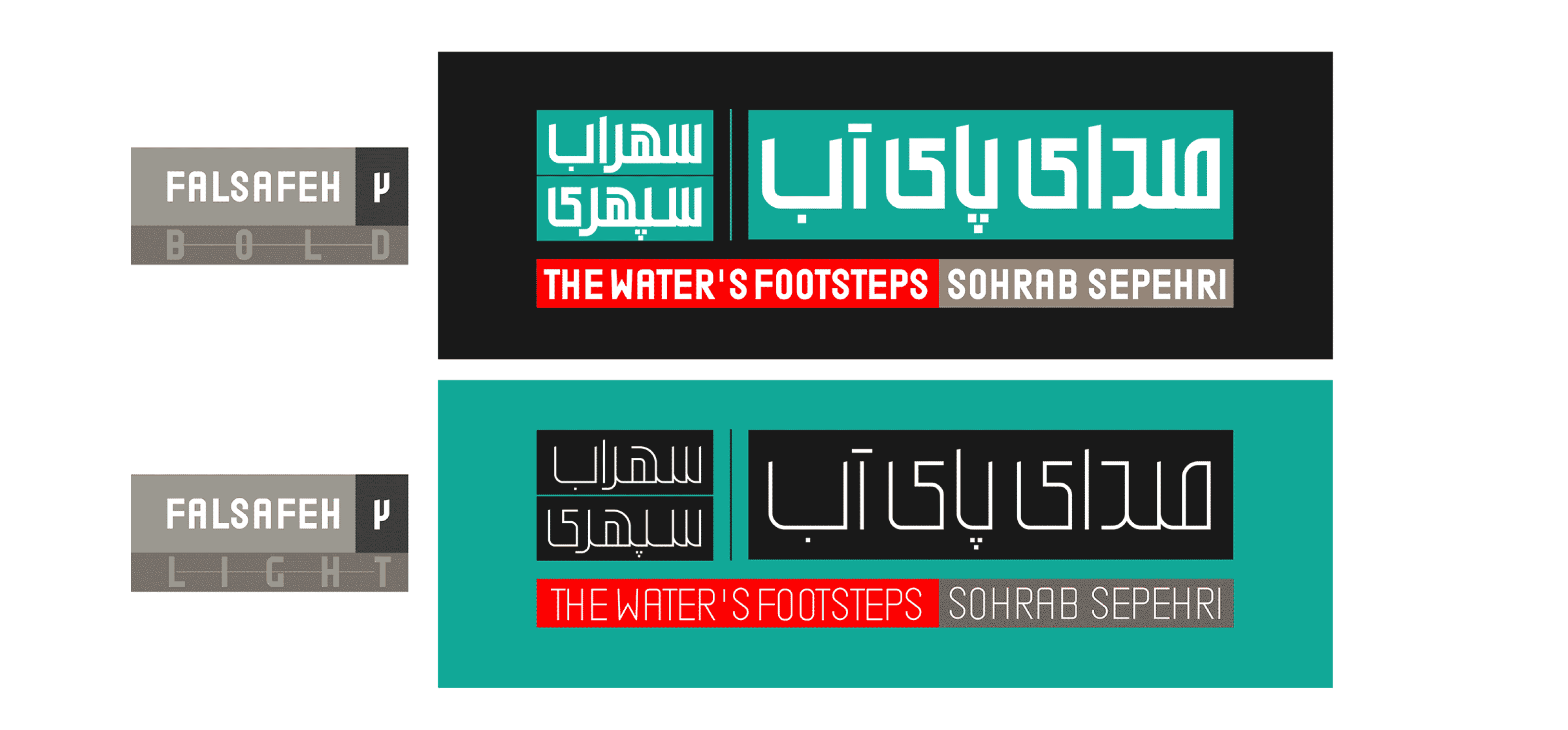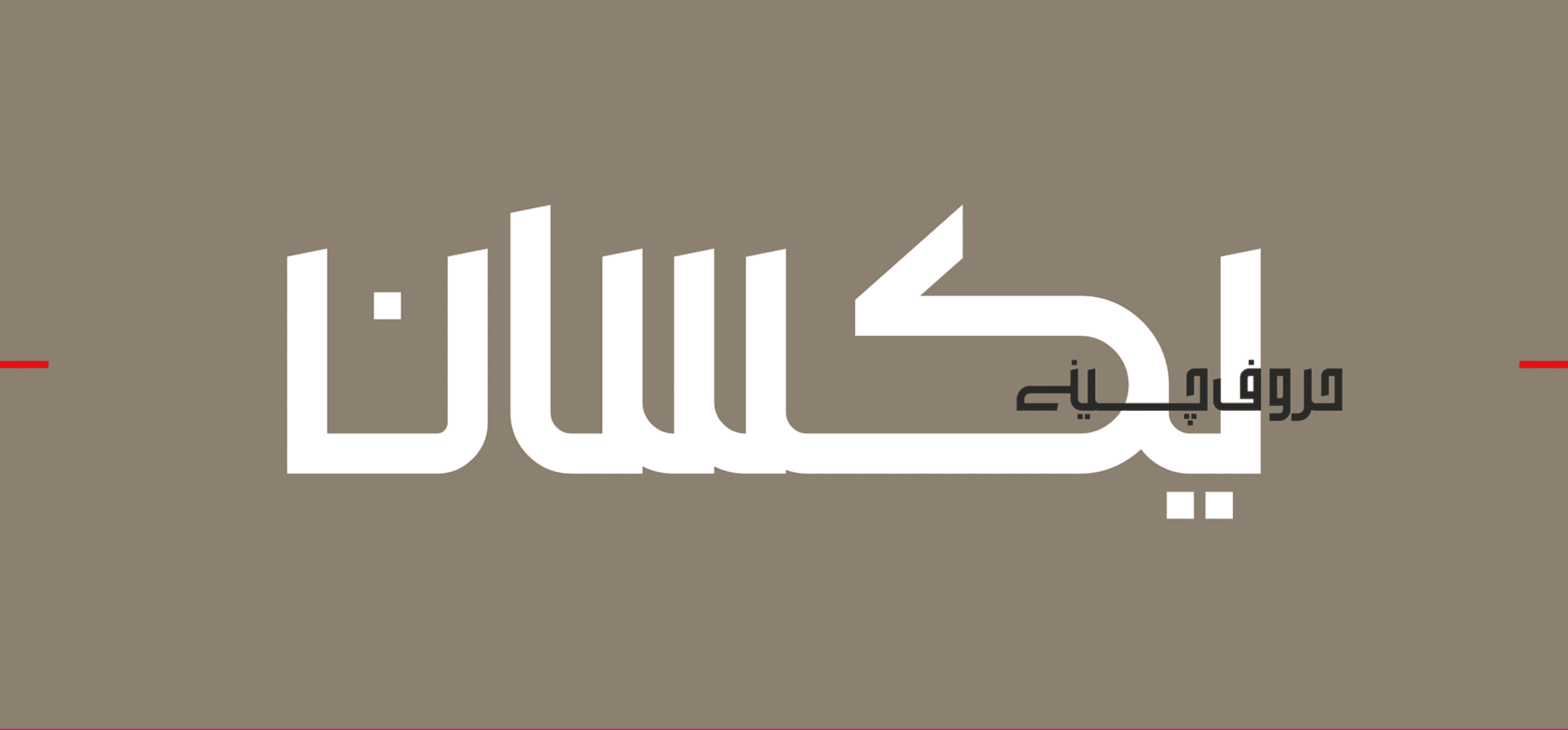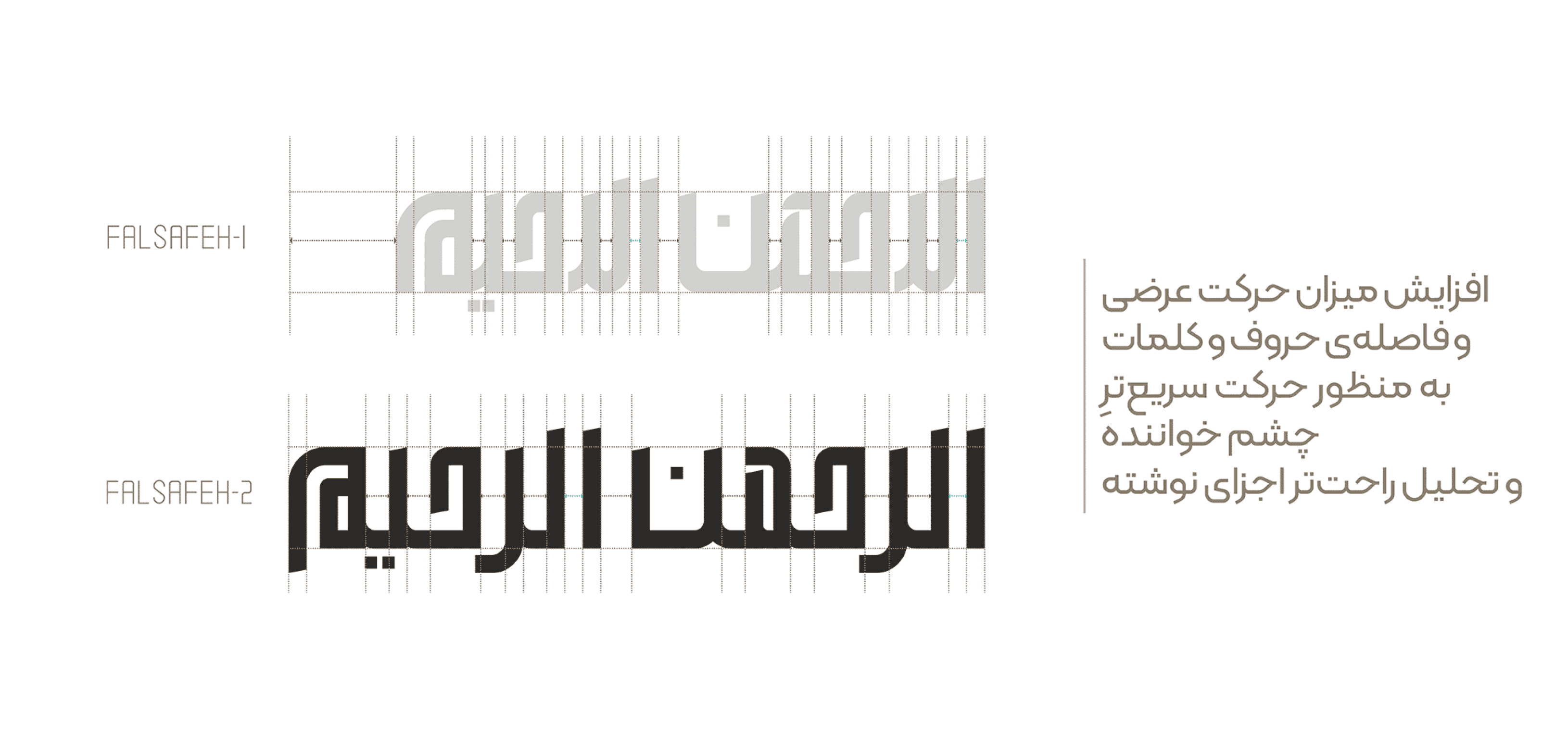
الهدف الرئيسي من تصميم خط "فلسفه" هو ابتكار خط فارسي بهيكلية هندسية ولمسة مميزة تختلف عن الخطوط التقليدية الشائعة.
ثمرة هذا التصميم تكمن في إضفاء حداثة على النصوص الفارسية، وتحفيز ذهن القارئ للتفاعل مع المحتوى. يمكن القول إن التحدي البسيط الذي يواجهه القارئ أثناء القراءة يجعل النص أكثر رسوخًا في الذاكرة، وهذه الاستمرارية تُعد من أهم عوامل إيصال الرسائل، لا سيما في السياقات الإعلانية.
الهدف الرئيسي من تصميم خط "فلسفه" هو ابتكار خط فارسي بهيكلية هندسية ولمسة مميزة تختلف عن الخطوط التقليدية الشائعة.
ثمرة هذا التصميم تكمن في إضفاء حداثة على النصوص الفارسية، وتحفيز ذهن القارئ للتفاعل مع المحتوى. يمكن القول إن التحدي البسيط الذي يواجهه القارئ أثناء القراءة يجعل النص أكثر رسوخًا في الذاكرة، وهذه الاستمرارية تُعد من أهم عوامل إيصال الرسائل، لا سيما في السياقات الإعلانية.
الهدف الرئيسي من تصميم خط "فلسفه" هو ابتكار خط فارسي بهيكلية هندسية ولمسة مميزة تختلف عن الخطوط التقليدية الشائعة.
ثمرة هذا التصميم تكمن في إضفاء حداثة على النصوص الفارسية، وتحفيز ذهن القارئ للتفاعل مع المحتوى. يمكن القول إن التحدي البسيط الذي يواجهه القارئ أثناء القراءة يجعل النص أكثر رسوخًا في الذاكرة، وهذه الاستمرارية تُعد من أهم عوامل إيصال الرسائل، لا سيما في السياقات الإعلانية.